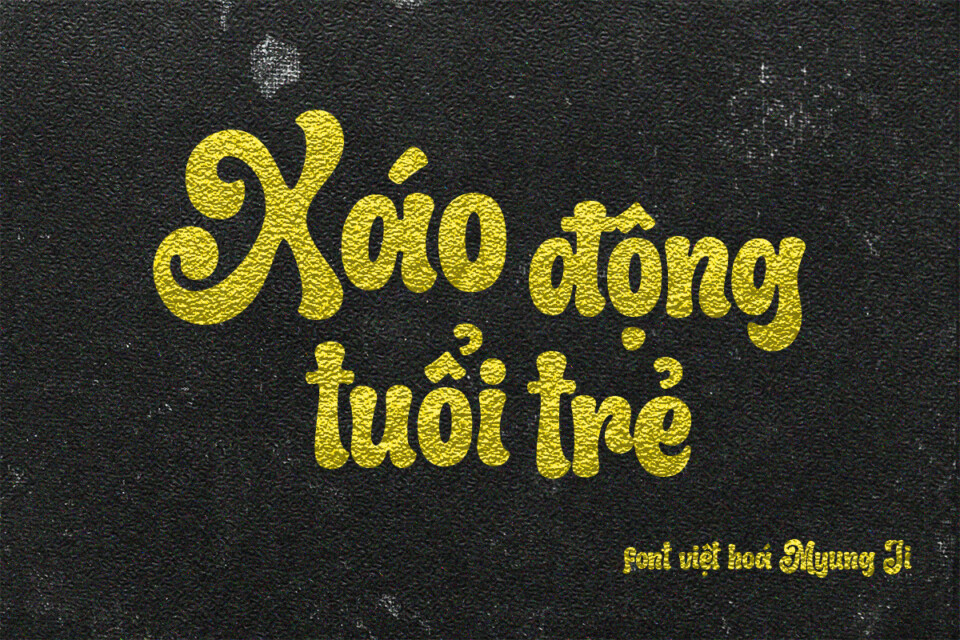
Giới thiệu về bộ Font việt hoá MJ Neighbor’s Blanket
Trong thế giới thiết kế đồ họa, việc lựa chọn một Font Chữ phù hợp đóng vai trò quan trọng trong việc truyền tải thông điệp. Font việt hoá MJ Neighbor’s Blanket là một bộ phông chữ mang phong cách thủ công, ấm áp và gần gũi, mô phỏng những nét vẽ tay mềm mại như những tấm chăn đan xen. Đây là lựa chọn lý tưởng cho các thầy cô giáo và học sinh khi thực hiện các dự án sáng tạo, làm bài thuyết trình hoặc thiết kế thiệp mời trong môi trường học đường.
Đặc điểm nổi bật của phông chữ
Bộ Font việt hoá MJ Neighbor’s Blanket sở hữu các đường nét tròn trịa, tạo cảm giác thân thiện và dễ đọc. Bản việt hóa đã được tối ưu hóa hoàn toàn hệ thống dấu tiếng Việt, giúp người dùng không còn lo lắng về lỗi hiển thị khi soạn thảo văn bản. Sự kết hợp giữa tính nghệ thuật và sự rõ ràng giúp bộ phông này trở nên nổi bật trên cả nền tảng kỹ thuật số lẫn in ấn.
Ứng dụng thực tế và cách sử dụng hiệu quả
Phông chữ này cực kỳ phù hợp cho các bìa sách giáo khoa, trang trí bảng tin lớp học hoặc các video bài giảng sinh động. Với phong cách nhẹ nhàng, nó giúp giảm bớt sự cứng nhắc của các văn bản hành chính thông thường, khơi gợi cảm hứng học tập cho các em học sinh.
Lưu ý khi thiết kế
Để đạt hiệu quả tốt nhất, bạn nên kết hợp phông chữ này với các tông màu pastel hoặc màu gỗ tự nhiên. Điều này sẽ làm tăng thêm vẻ đẹp mộc mạc và chân thực của thiết kế. Hãy chú ý khoảng cách giữa các chữ cái để đảm bảo văn bản luôn mạch lạc và chuyên nghiệp.
Kết luận về bộ phông chữ MJ Neighbor’s Blanket